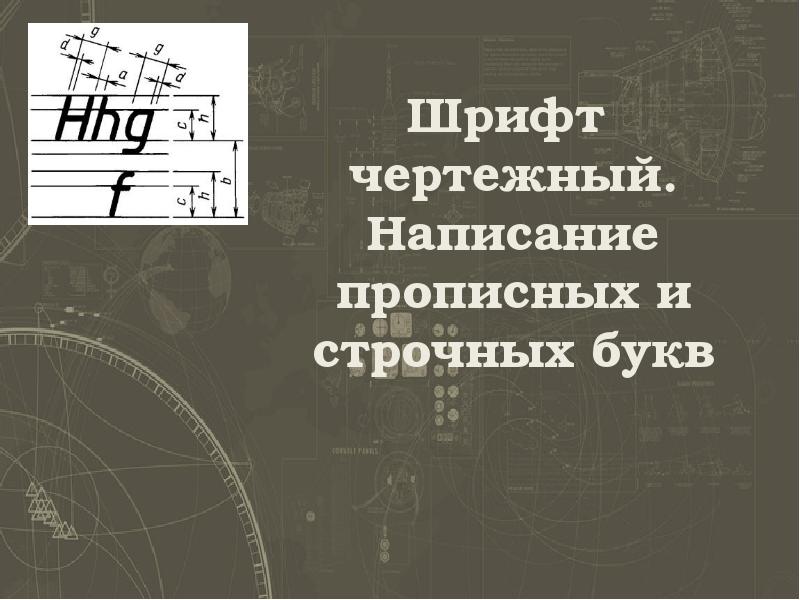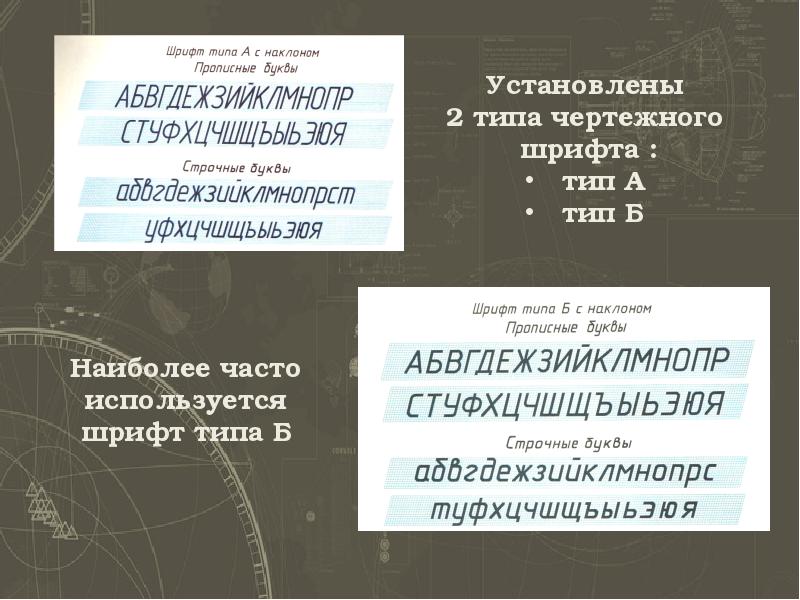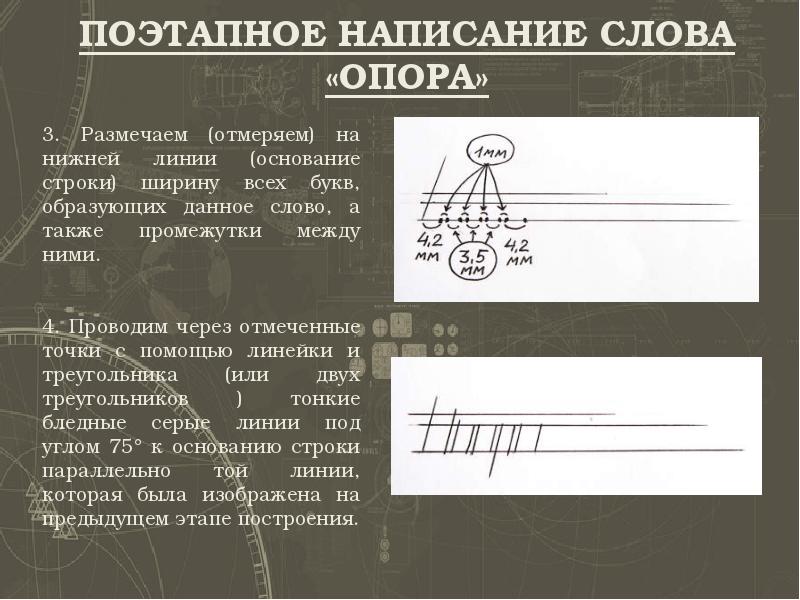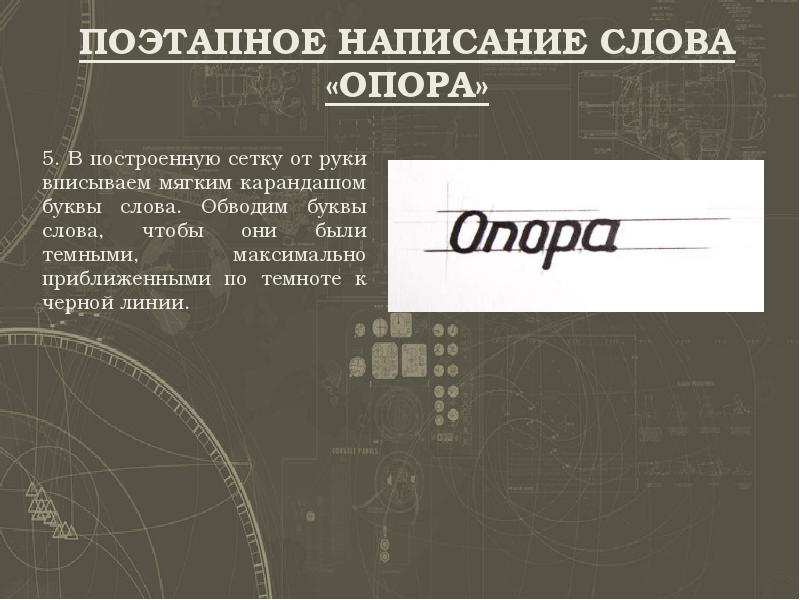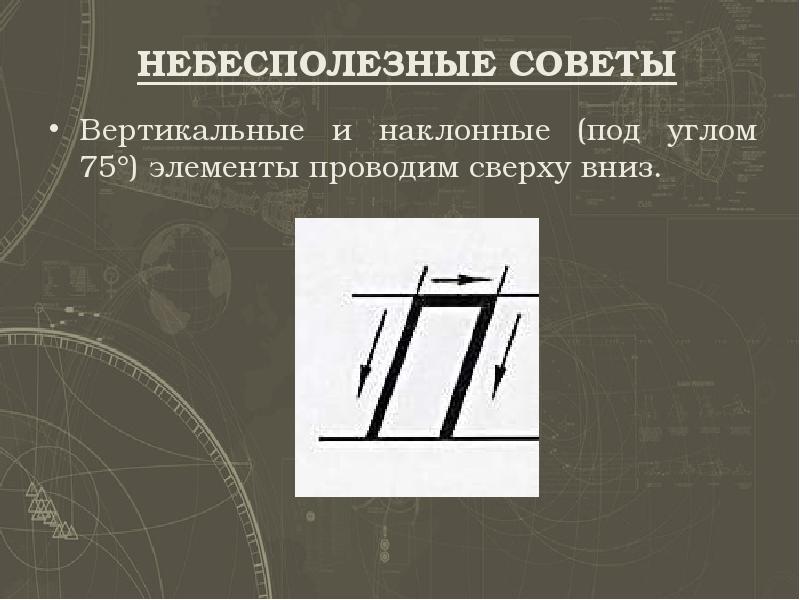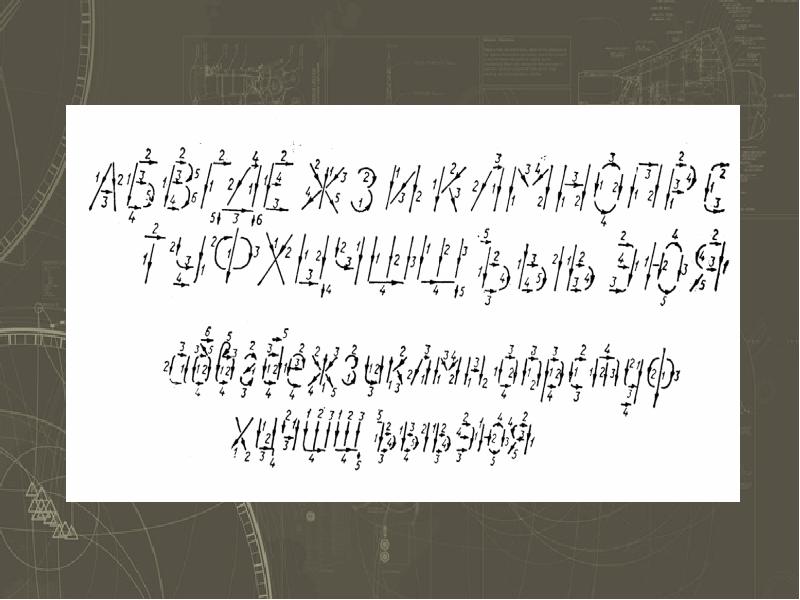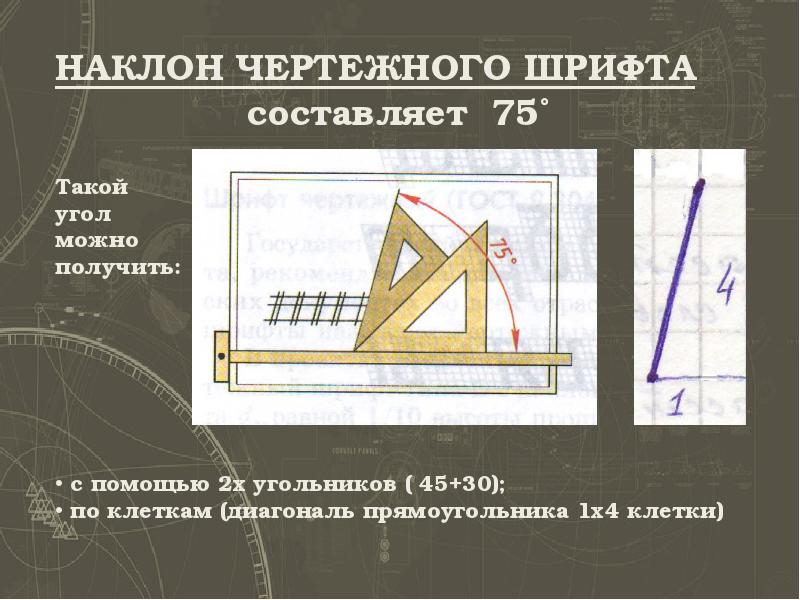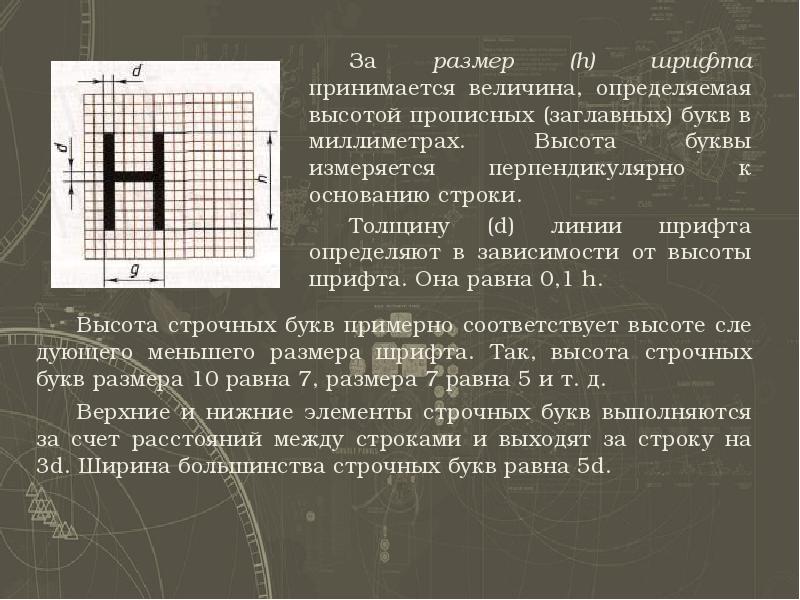
ШРИФТ ЧЕРТЕЖНЫЙ ГОСТ 2.304 - 81 Все надписи на чертежах должны быть выполнены чертежным шрифтом. Начертание букв и цифр чертежного шрифта...
ШРИФТ ЧЕРТЕЖНЫЙ ГОСТ 2.304 - 81 Все надписи на чертежах должны быть выполнены чертежным шрифтом. Начертание букв и цифр чертежного шрифта устанавливается стандартом. Стандарт определяет высоту и ширину букв и цифр, толщину линий обводки, расстояние между буквами, словами и строчками. Стандарт устанавливает следующие размеры шрифта: 1,8 (не рекомендуется, но допускается); 2,5; 3,5; 5; 7; 10; 14; 20; 28; 40.
НАКЛОН ЧЕРТЕЖНОГО ШРИФТА
РАЗМЕР ЗАГЛАВНОЙ БУКВЫ